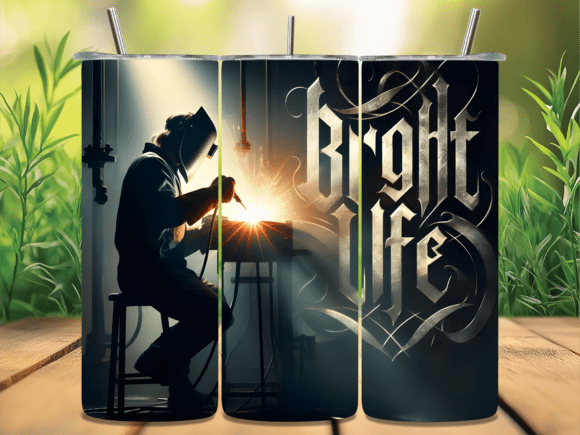
Welder Bright Life Gothic Font Tumbler
Việc tìm kiếm các thành phần thiết kế phù hợp có thể là một thách thức, nhưng Welder Bright Life Gothic Font Tumbler cung cấp một bộ sưu tập đặc biệt giúp nâng tầm công việc của bạn ngay lập tức.